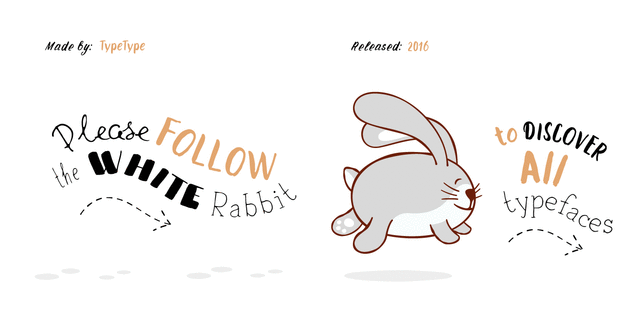
TT Rabbits – сверхэмоциональное рукописное шрифтовое семейство, состоящее из 10 разных шрифтов. Мы объединили эти шрифты по одной общей теме – детство. Используйте эти шрифты для создания любой продукции для детей – детские книжки, приложения для детей, интерьеры детских комнат.
Мы дали каждому кролику уникальное имя. Имена выстроены по буквам латинского алфавита: A — April, B — Bro, C — Chilli, D — Dummy, E — Elf, F — Fatso, G— Goody, H — Hyper, I — Idol, J — Junior. Каждый кролик имеет свой характер, поэтому вы определенно полюбите TT Rabbits. Мы использовали индивидуальный пишущий инструмент для каждого шрифта. Все шрифты изначально создавались на бумаге, а затем оцифрованы.
А какой ваш любимый кролик? Шрифт разработан Иваном Гладких в студии TypeType Fonts в 2016 году.
лихой, дикий, динамичный, подвижный, неряшливый, нервный, ремесленный, жаркий, знойный, южный, наивный, грубый, забавный, прикольный, рукотворный, остроумный, веселый, игривый, оригинальный, карикатурный, мультяшный, живой, характерный, неровный, праздный, гуляющий, вкусный, зеленый, натуральный, природный, теплый, ламповый, аппетитный, свежий, сочный, спелый, домашний, озорной, кустарный, самодельный, артистичный, органический, милый, симпатичный, тропический, вернакулярный, свободный